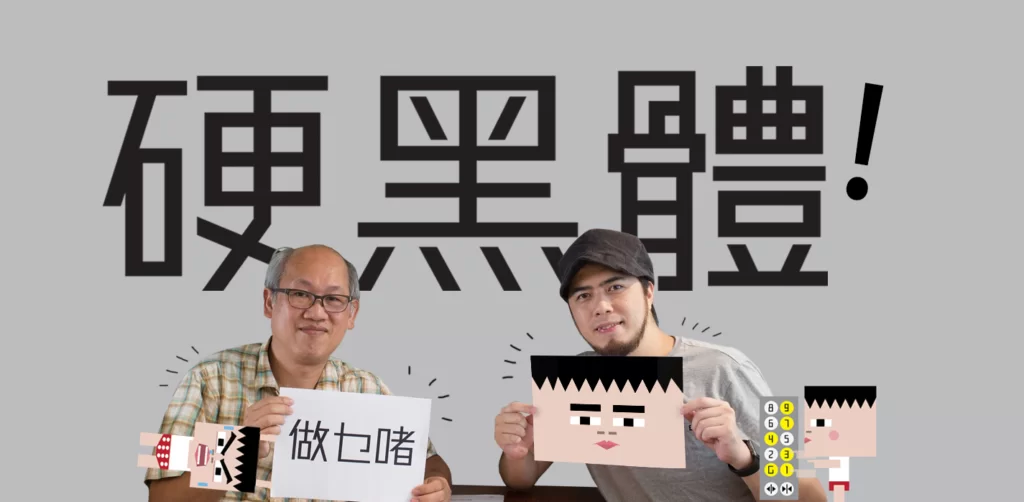
以近二千五百天的腦力、眼力、指力勞動總和,換來不足一百人課金支持。硬黑體設計師阮慶昌(Eddie)苦笑道:「Sam Hui都唱啦,出咗半斤力,未必可以攞番足八両嘛!」頭髮略帶花白的Eddie已近花甲之年,是一位無後台的獨立中文字體設計師。青春小鳥縱然遠去,但血仍然熱到燙手。回帶到1997年,他花了五年時間單人匹馬造出一套有五千多個常用字的「硬黑體」。二十個月前他動工重繪字體,還添上千多個「香港字」,數周前新版面世,雖然推出多項優惠,包括五折價500元,銷情卻一如十多年前,慘淡也。
阮慶昌形容硬黑體「尖銳,挻直,堅硬」。
2002年買家三十二人,2018年暫為四十九人。一夫操機,萬字造出,七年滋養,支持者就只八十一。他豁達笑謂:「推出新版後,太太問我目標是多少,我答她夠五十個我哋就去食一餐慶祝。」慶功宴仍然無期。他指字體最少要有四、五百人買才能封蝕本門。孤身造字,時間成本高,想在香港賴以維生,等同玩命。「台灣字體公司justfont造一套字,兩位設計師加上助手合力,都要造兩年以上。我都想好似Kitman的勁揪體有七百幾人支持,話不想是騙你的,但每個人條件唔同。」
新版硬黑體改了部分字的寫法,兩個寫法將來會提供給用家挑選使用。
剛直字體初現
硬黑體2002年首度推出,他謂當時市場沒類似字體,而且比較易造。「蒙納公司的剛黑體五六年前才推出。我喜歡黑體字型起角硬朗,那時也喜歡圓體,可是圓體筆劃多曲線,處理節點會較多,要花更多時間。」造字起頭難,難在當時他手拿的是造英文字體的軟件。「花很多時間摸索點做,那時科技不先進,要先查詢每個字的大五碼內碼是什麼,逐字輸入。然後把字的部首偏旁畫好再掃描,組合成不同字,在軟件內調節字型比重……」那是同時開幾個檔案,電腦已吃不消要回氣的年代,也是56K上網隨時斷線的年代。如是者,他日出而作,日入再作,歷經五個寒暑造出了「硬黑體」。他憶述那時宣傳渠道就是香港及台灣的網上論壇。「三十二個買家有一半都非香港人,有外國人,有美國華人。」
Eddie於大一設計學院讀平面設計,後來任職於指示牌公司。08年起自立門戶,為建築物造水牌、凸字牌、路標等。「這些牌用現成電腦字體,沒什麼創作成分。我最多只是執漏,微調筆劃粗幼等。」穩定的工作讓他無後顧之憂投入浩瀚的造字工程。「那時心想如果造出來的字成功的話,自己有多條路,唔成功都仲有份工。」
年少時他在報上閱到知名平面設計師蔡啟仁憑字體設計拿到獎項,驚覺字體如斯有趣,從此變成「字戀狂」。「佢又上報紙又上電視,因為好少人琢磨中文字體設計範疇。」那個年代參考書不多,只有兩三本台灣出版的字體設計書。「那時死慳死抵買日本字體書,一本要成五六百元。」
硬黑體2.0 新增了一千零九十四個香港常用字,包括赤鱲角的「鱲」字、深水埗的「埗」及鰂魚涌的「鰂」。
以往很多「香港字」不能輕易鍵入輸出,阮慶昌認為身為香港人,不造這些字說不過去,所以新版先造香港字,大五碼的次常用字他仍在努力中。
遇上通書硬黑體
花了五年時間向字體示愛,卻落得銷情慘淡。以為硬黑體再無下文,事隔十多年,他居然在書店看到一本採用硬黑體排版的書。「看到Albert的《香港人自作業》好感動,書內每個字都用自己用心做的字體,真係幾乎流眼淚。後來我聯絡他,他說想付費購回。但我重看那套字體,覺得好醜,收錢自己也不好意思。」遇上知音的Eddie,帶着對美感的堅持,決定為字體「整容」。「我發現少少少少咁執,無辦法執得靚,一定要大改,於是就由零開始重新再畫再造。有上次經驗,2.0係比較好。」DDED設計師Albert經常在專頁借「起角」動畫及插圖靚抽時事,所用的字體正是硬黑體舊版。「2014年創作DDED就開始用這隻字,嗰時想買已搵唔到途徑。」舊版無香港字,但偏偏DDED的創作十分地道,常用口語,為何仍要硬用硬黑體?「因為真係好鍾意,字體線條簡單,夠硬又起角,無誇張的勾。我的圖用最少graphics模擬物件,無多餘裝飾,字體同我嘅創作風格好夾。開頭用都痛苦,經常要自造香港字。」Albert指他用了硬黑體後,多了設計師採用。他笑說:「開專頁後,好多人問我用嘅係咩字體,無人關心我的創作同自身。」DDED專頁銷「膠趣味」,方方正正的人物有時「曲到圓」。我問Eddie是否明白他的「幽默」。他笑說:「多啲同個仔傾偈就明。」DDED搶問:「有無覺得我用影衰你隻字?」「設計師就係要將字體不同特質發揮出來,我太循規蹈矩,這樣撞出火花我覺得OK。」
DDED設計師Albert(右)認為阮慶昌的硬黑體雖為十多年前的設計,但今時今日看絲毫不覺老土,認為它簡練的筆劃可以橫跨時代。
DDED設計師Albert的這本著作讓阮慶昌熱淚盈眶,推動他更新十多年前開發的硬黑體並重推市場。
起角公仔與硬直字體,異常匹配。圖中的「㩒」、「𨋢」、「攰」、「掹」、「嘥」及「嘢」都是硬黑體2.0新增的香港字。
有人欣賞並不代表帶來實利,Eddie發現這些年來很多廣告或大品牌都用他的字體,但到底有多少是真金白銀購買,無從稽考。「用得最多應是麥當勞,另外還有九巴、蘇寧等。或者設計師之前真的買了來用。又或者有人不知在哪裏『承繼』返來,好難查證。」字體盜用猖獗,可是獨立設計師根本無力追究。「經濟上唔容許我提告,要華康這種大型字體公司才有資源發信叫人付版權費。」他提到justfont字體用軟件防盜,沒付錢的人使用會被阻止。「不論如何精密,黑客一樣拆到,戰爭永遠都在。只看使用者有沒有版權意識。」
多年來,Eddie「野生捕獲」不少廣告、品牌宣傳品都採用硬黑體,證明字體有市場價值,可惜沒為他帶來實利。
2.0版沒公司客戶
除了在Facebook開專頁弱弱地宣傳,Eddie也主動出擊接觸目標用家。「太太花了幾天將全港所有設計、廣告及印刷公司電郵地址找出來,寄出三四百封電郵,但我看買的人都沒用這些公司電郵。」他感激不少人因支持他開發字體而購買,但估計當中八成人根本不會使用字體。「無公司買是失望的,當然他們可能覺得唔靚而唔買,但如果你不支持這個創作產業,日後能用的設計資源只會更少。」花心力造字,無人買加被盜用兩面夾擊,創作人難道真能靠光合作用生存?
台灣的金萱體與香港的勁揪體都是眾籌成功的例子。推出硬黑體2.0前,Eddie都想過眾籌。他笑說:「Albert一盤冷水淋落來,話Kitman眾籌前已出名,眾籌好講知名度。的確金萱眾籌前都有辦展覽及講座推廣,這些要一個團隊去做,我什麼都沒有。」如果市場健康,創作人單靠有需要人士購買便足夠餬口,當然皆大歡喜,可是現實不如人意。「眾籌始終不是賣字體的正途,大家應是有需要才買。可惜沒什麼平台讓創作人寄賣。外國有myfonts.com,但抽佣抽50%;日本字體公司要求你要有日本地址;台灣的justfont就回覆他們主要考慮內文字款,覺得硬黑體像標題字。我都明白如果通篇好密好多字,可能會睇得唔舒服。」金萱體讓台灣人自豪出色字體不一定往日本外求,更讓人了解用新字體要付出代價,但代價並非想像中大。繼續默默密密造次常用字的Eddie或許是愚公,但信終有一天能攞番足八両。